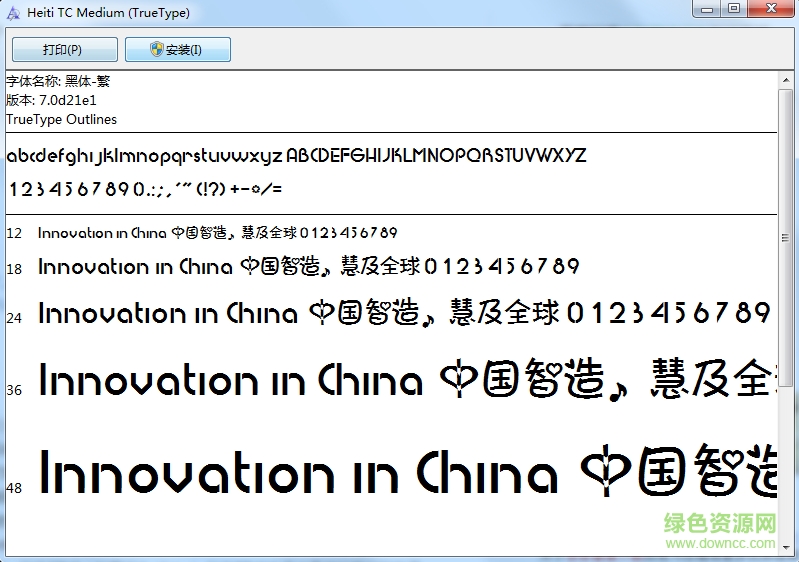
小清新字體是一款充滿了各種心形造像和音符點(diǎn)綴的藝術(shù)字體,讓你的文字顯得更為輕松活潑,支持繁體中文輸入,黑體模板更顯大方搶眼,綠色資源網(wǎng)誠意推薦!
小清新中文字體是一款可愛心形小清新中文字體本作品可用于廣告設(shè)計(jì)字體、網(wǎng)頁設(shè)計(jì)字體、包裝設(shè)計(jì)字體、屏幕顯示字體等。
小清新中文字體采用了心形和音符來修飾文字,在字里行間顯得活潑生動,滿足你的小清新個性,可用于多種場合,歡迎免費(fèi)嘗試哦!商務(wù)使用還請去官網(wǎng)授權(quán)哦!